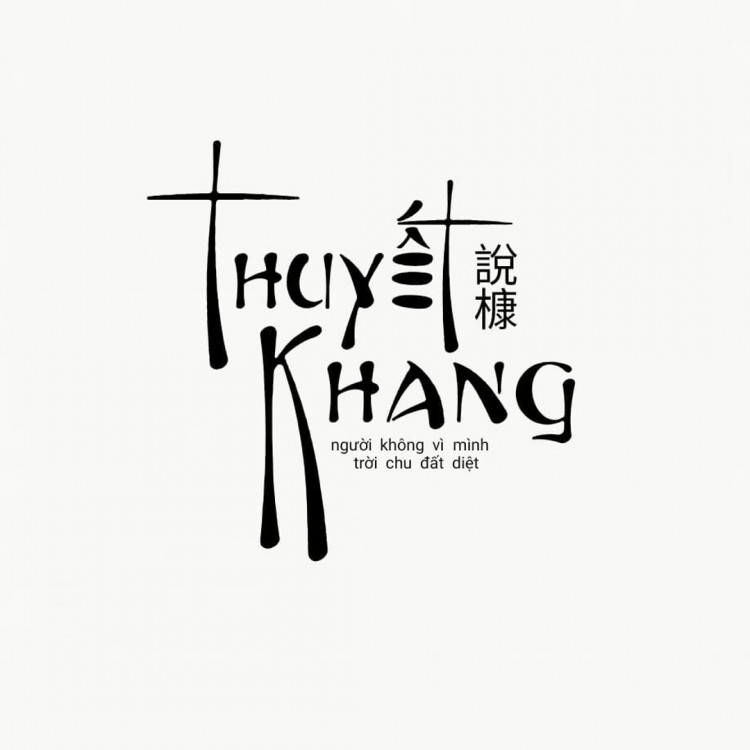
Giới thiệu về Font việt hóa LNTH Fontasia
Trong thế giới thiết kế đồ họa, việc lựa chọn một bộ Font Chữ phù hợp đóng vai trò quan trọng trong việc truyền tải thông điệp. Font việt hóa LNTH Fontasia là một cái tên nổi bật, mang đến phong cách cổ điển kết hợp hơi thở hiện đại. Đây là lựa chọn hoàn hảo cho các bạn học sinh, sinh viên và giáo viên muốn tạo ra những bài thuyết trình hay tài liệu học tập ấn tượng. Với đường nét thanh thoát và bay bổng, bộ font này giúp mọi dự án sáng tạo trở nên chuyên nghiệp hơn bao giờ hết.
Tại sao nên sử dụng Fontasia cho thiết kế?
Đặc điểm nổi bật của Font việt hóa LNTH Fontasia chính là sự tỉ mỉ trong từng nét vẽ. Các ký tự được tối ưu hóa hoàn toàn cho tiếng Việt, giúp người dùng không còn lo lắng về lỗi hiển thị dấu câu. Sự linh hoạt của nó cho phép ứng dụng trong nhiều lĩnh vực như thiết kế thiệp mời, bìa sách, hoặc các ấn phẩm truyền thông học đường. Bên cạnh đó, tính thẩm mỹ cao giúp người xem dễ dàng bị thu hút ngay từ cái nhìn đầu tiên.
Kết luận về bộ font nghệ thuật này